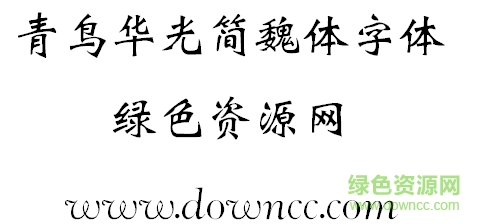
青鳥華光簡魏體是根據(jù)魏碑字體創(chuàng)作而來的藝術字體,字跡保留了魏體的飄逸古風感,更有古法書寫的得體和大方韻味,歡迎大家來綠色資源網(wǎng)免費下載使用哦!
青鳥華光簡魏體繼承了魏體的穩(wěn)健而灑脫之風,字跡伶俐不拖沓,筆畫連貫而流暢,很適合某些廣告創(chuàng)意、平面設計等場合。
魏體橫畫和捺畫保持隸書的特點,常伸展到字形邊界甚至超出邊界, 突出的特點是撇捺向兩側伸展,收筆前的粗頓以及抬峰,使整個字形厚重穩(wěn)健略顯飛揚、規(guī)則中正而有動態(tài),頗具審美價值。字形與隸書相比呈扁方形。